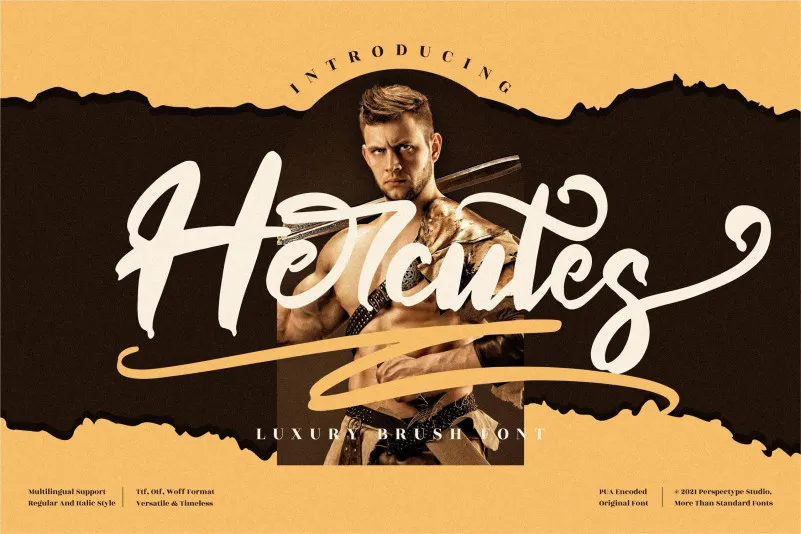
Hercutes Font é uma nova adição à nossa seleção de futas brush script modernas e bold, criada pelo designer perspectype. Este tipo de letra possui um estilo personalizado perfeito para aplicar em diversas criações gráficas, como cartões de convidado, convites de casamento, cartazes de aniversário, logotipos e muito mais. Caracterizada pela sua codificação PUA (Proprietary Unicode Association), que permite acesso a todos os caracteres e swashes de uma maneira simples e eficiente, Hercutes Font é ideal para criar um visual único e distintivo em suas próximas criações gráficas. Seja você criando cartões de convidado personalizados ou artigos de logotipos elegantes e sofisticados, esta fonte será a escolha perfeita para adicionar uma personalidade única ao seu projeto.